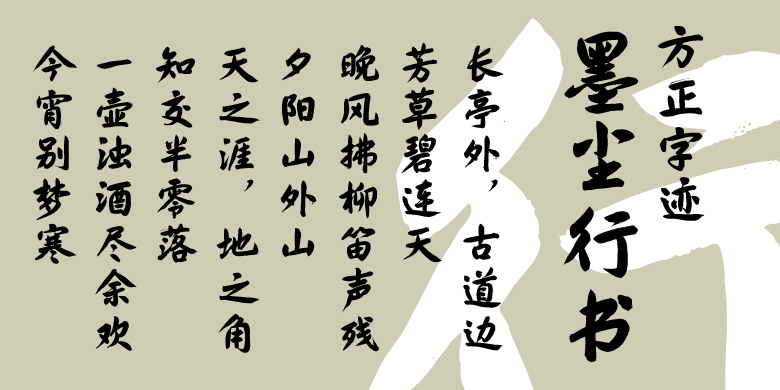
方正字迹-墨尘行书
自在飞花轻似梦
三更灯火五更鸡,正是男儿读书时。
黑发不知勤学早,白首方悔读书迟。
贺飞
行书、常规书写·毛笔
墨尘行书,是作者贺飞继《贺飞行楷》《贺飞行草》《墨尘榜书》《墨尘美楷》《墨尘榜隶》之后的又一潜心之作。该字体在行书结字造型的基础上,运用篆籀笔法使字体表现出圆润道劲、饱满浑厚和婉转流畅的线条。使之自然风雅、富有动感,能更好地迎合现代人的审美。适用于品牌、海报、杂志、书籍、包装、广告、招牌、新媒体等各个领域。